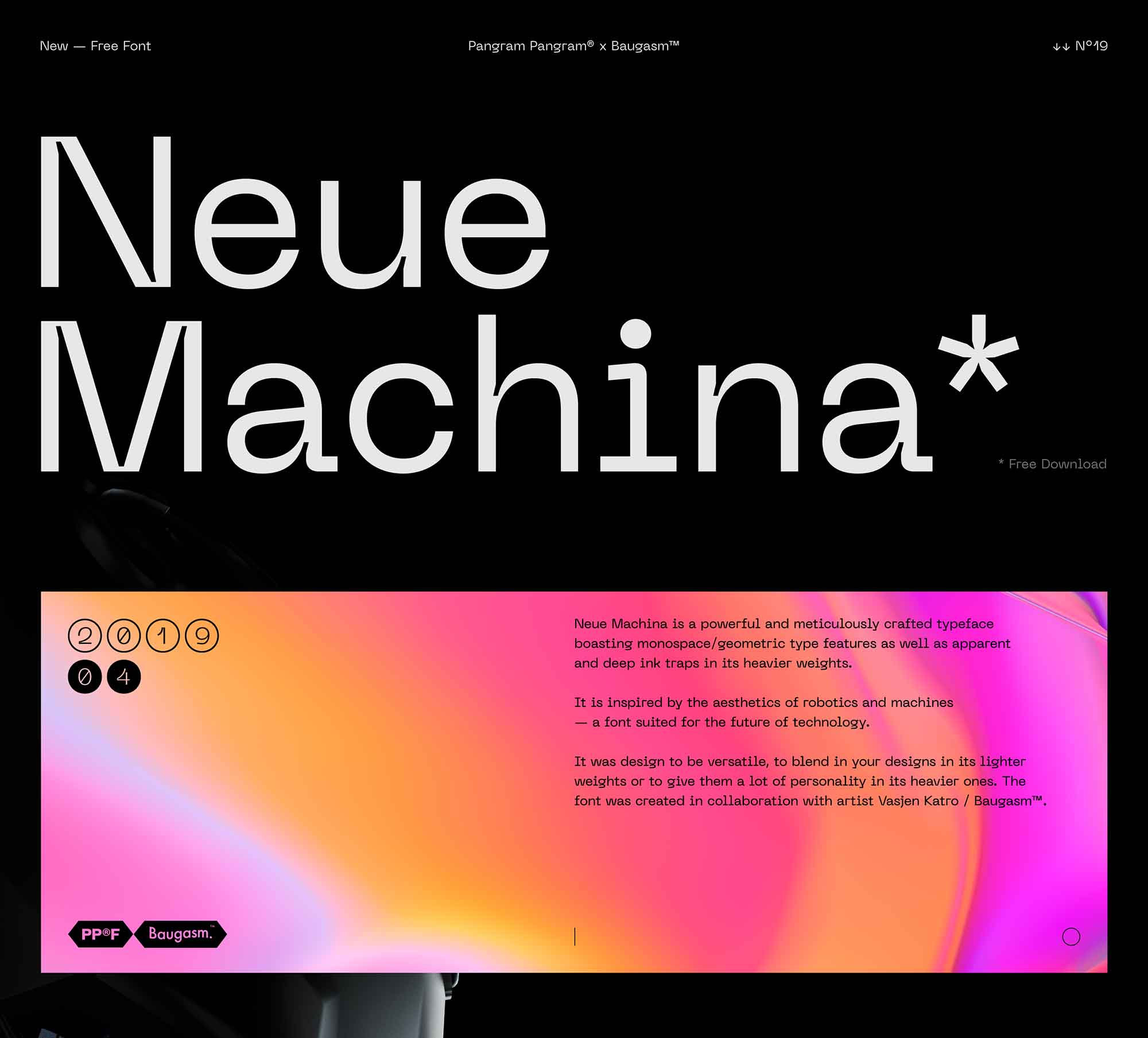
Neue Machina Font – Download Grátis
Neue Machina é uma fonte geométrica mono-espaço inspirada em tecnologia, máquinas e robôs. A fonte excepcionalmente bonita oferece sete pesos de tipo, de leve até grosso (Ultra light, light, regular, medium, bold, ultrabold, e black). Esta fonte conta com todos os 544 gílios, incluindo caracteres latinos básicos e extensos, números, símbolos e pontuação. Cada caractere segue um estilo consistente, combinando em harmonia para criar a beleza do texto impresso nessa fonte. Este recurso gráfico é ideal para designers de interfaces de usuários, desenvolvedores de jogos ou qualquer aplicação que necessite de uma fonte monocórdia e robusta, especialmente quando a temática tecnológica e futurista é essencial.